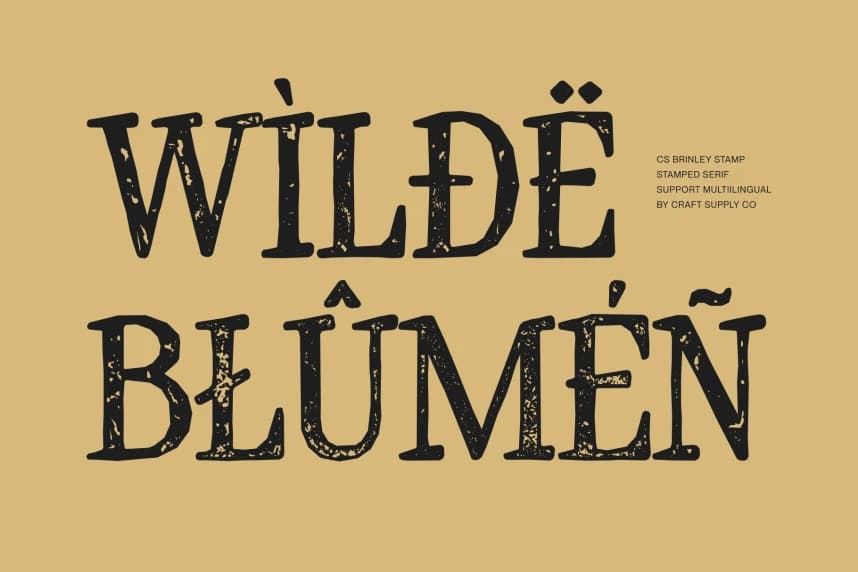
CS Brinley Stamp Font
CS Brinley Stamp Font – Dokulu Zarafetle Zamansız Serif. Modern Dokunuşla İncelikli Zarafet. Bu, klasik zarafeti çağdaş hassasiyetle sorunsuz biçimde harmanlayan modern bir serif yazı tipidir.
CS Brinley Stamp Font – Zamansız Serif, Dokulu Zarafet ile. Modern Dokunuşla Rafine Zarafet. Bu, klasik sofistike ile çağdaş kesinliği sorunsuz bir şekilde birleştiren modern bir serif yazı tipidir.